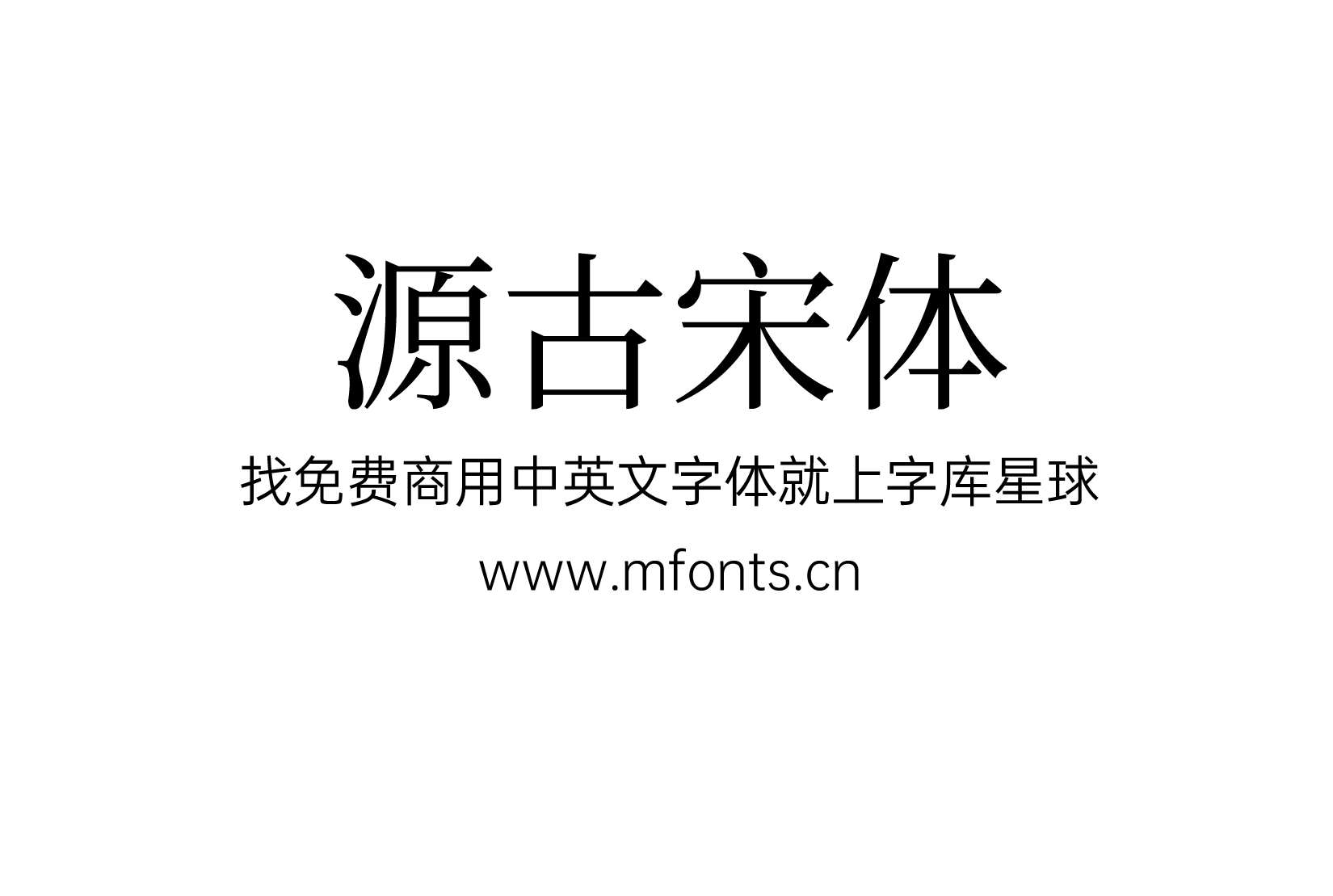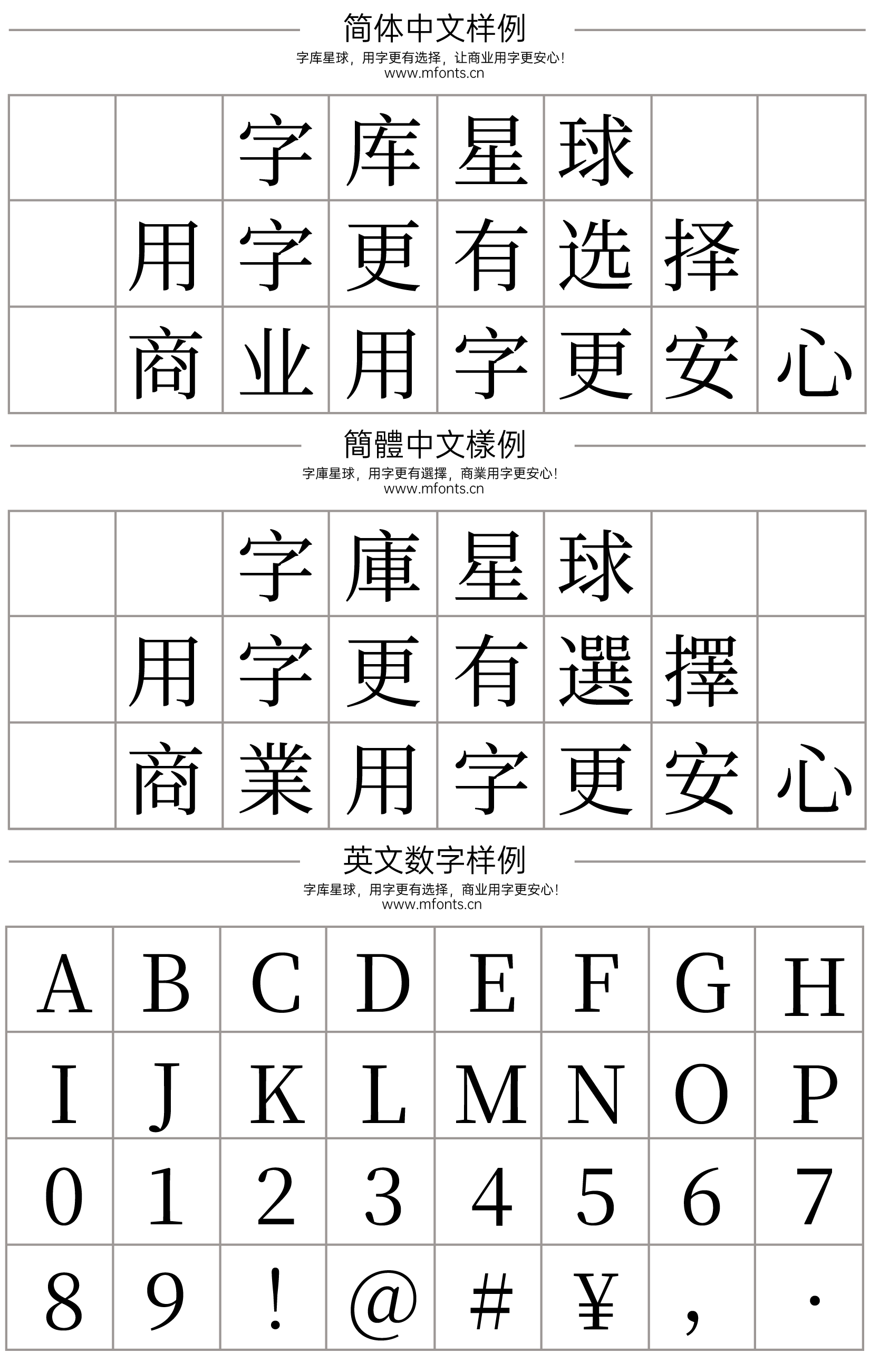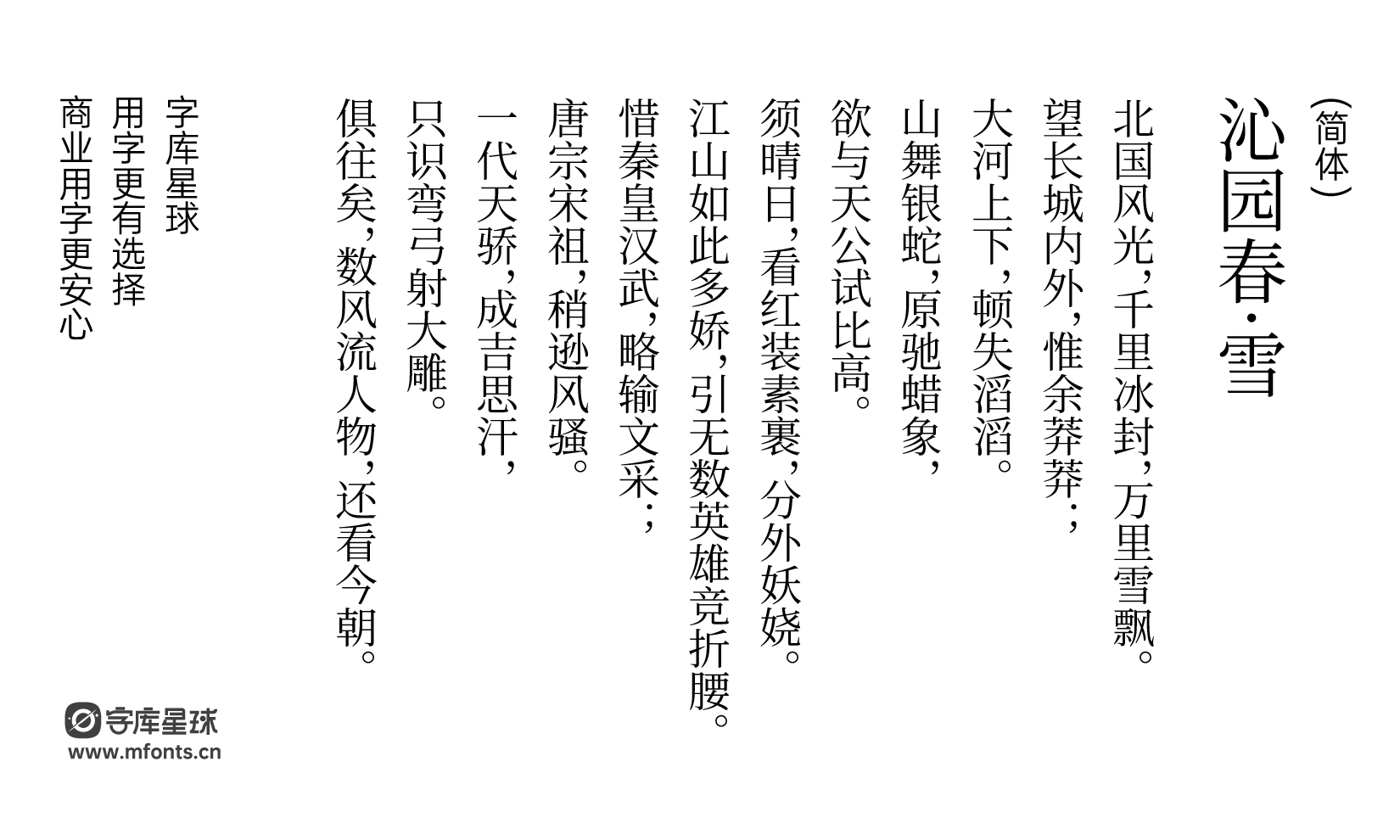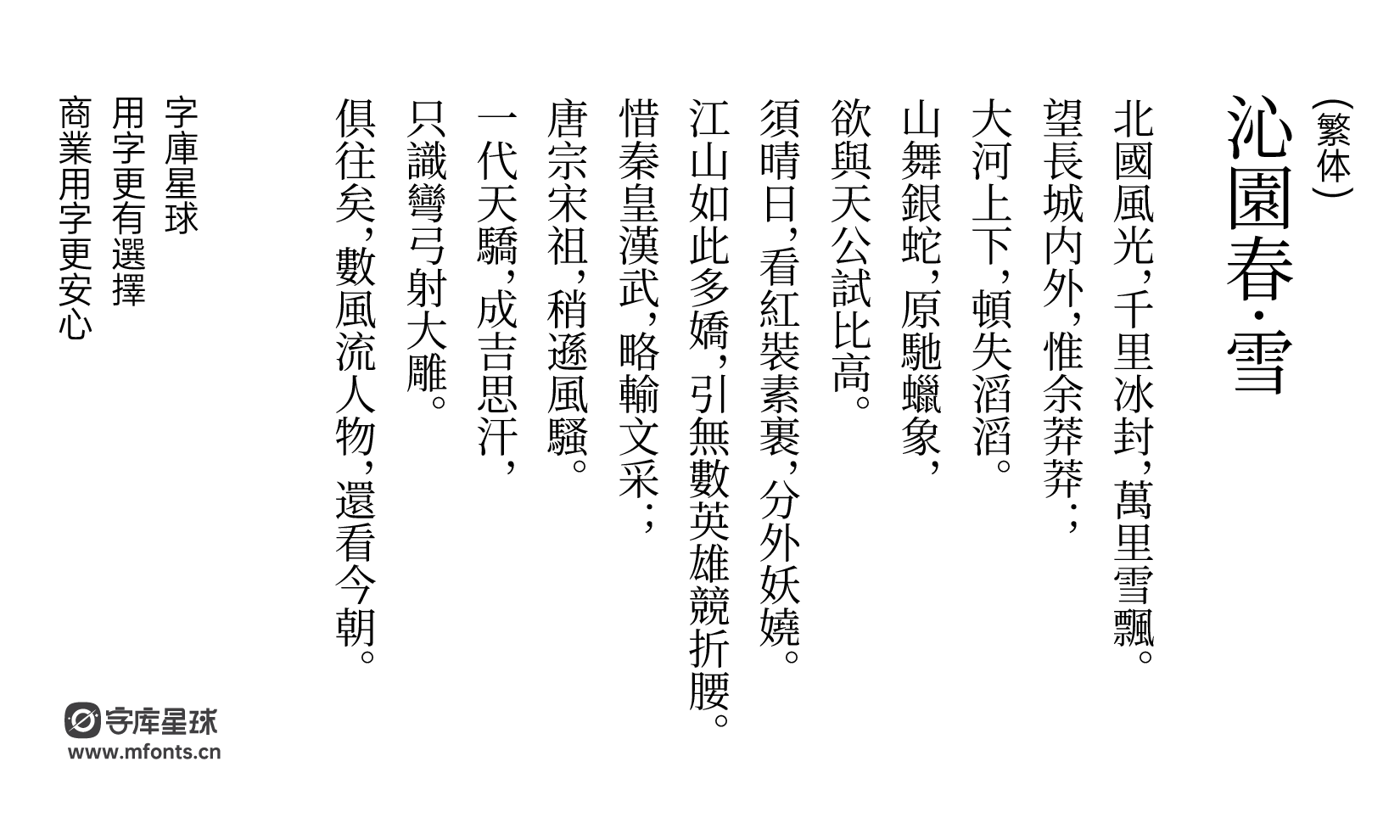
源古宋体
源古宋体是一款基于思源宋体改造,扩B区的字取自文津宋体,得益于思源丰富的地区字形,拆拆凑凑很方便就可以改出一个古籍表版本。而关于那些部件不统一的字,我有选择性地擅自进行了统一。
然后黑体和宋体各提供了两个版本,一个是仅包含古籍表表内字的纯古籍表版,一个是把古籍表外的——思源本来有的那些字一股脑放进去的“F”版本(当然这些表外字就没有按古籍表规范修改,保持思源原样)。
源古宋体
如果要作为做字体的参考或者炼丹的底子,就可以用纯古籍表版,以免被表外字误导。
(没错,其实这次弄这俩字体,本来就是作为炼丹工具性质的